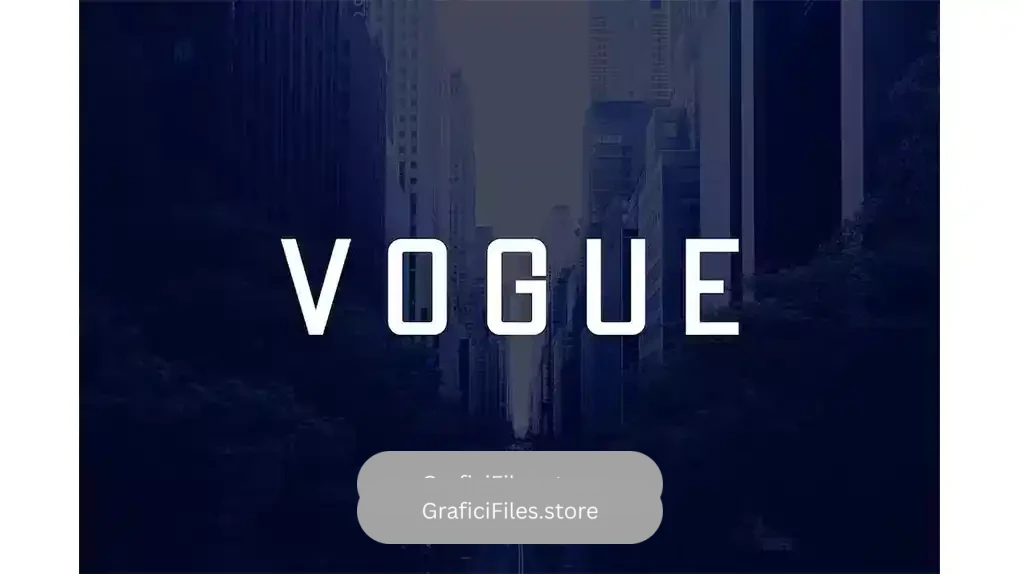
دانلود فونت انگلیسی مدرن VOGUE – Modern Display / Headline / Logo Typeface
فونت انگلیسی مدرن VOGUE : این مجموعه شامل یک فونت انگلیسی مدرن است که برای تیتر، برندینگ، لوگوتایپ، محتوای تبلیغاتی و گرافیکی مناسب میباشد.
مشخصات دانلود فونت انگلیسی مدرن VOGUE – Modern Display / Headline / Logo Typeface :
• عنوان مجموعه: VOGUE – Modern Display / Headline / Logo Typeface
• سبک: Sans-Serif
• فضا بین حروف: معمولی، متراکم، با فاصله
• اندازه بهینه: بزرگ (نمایش / پوستر)